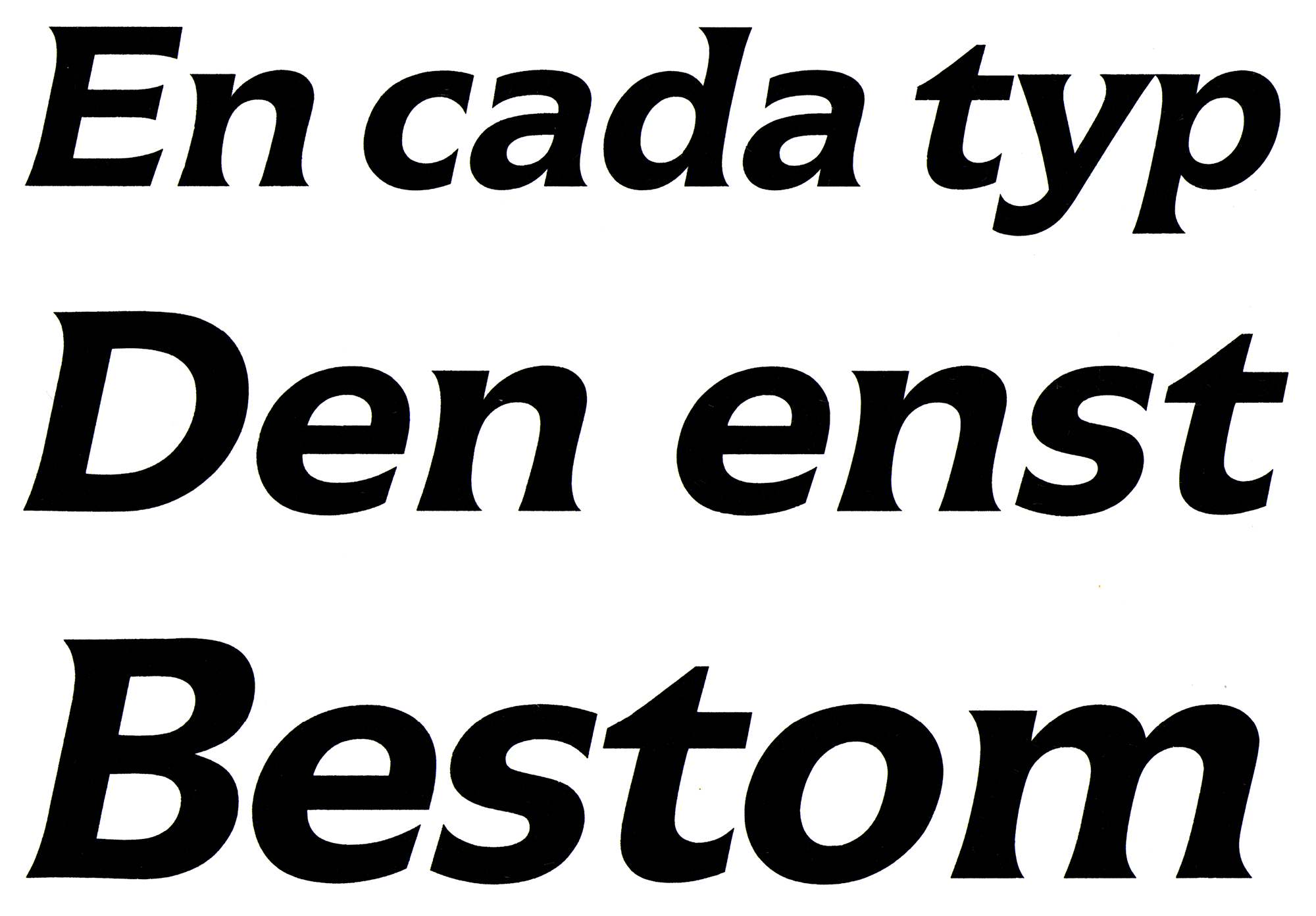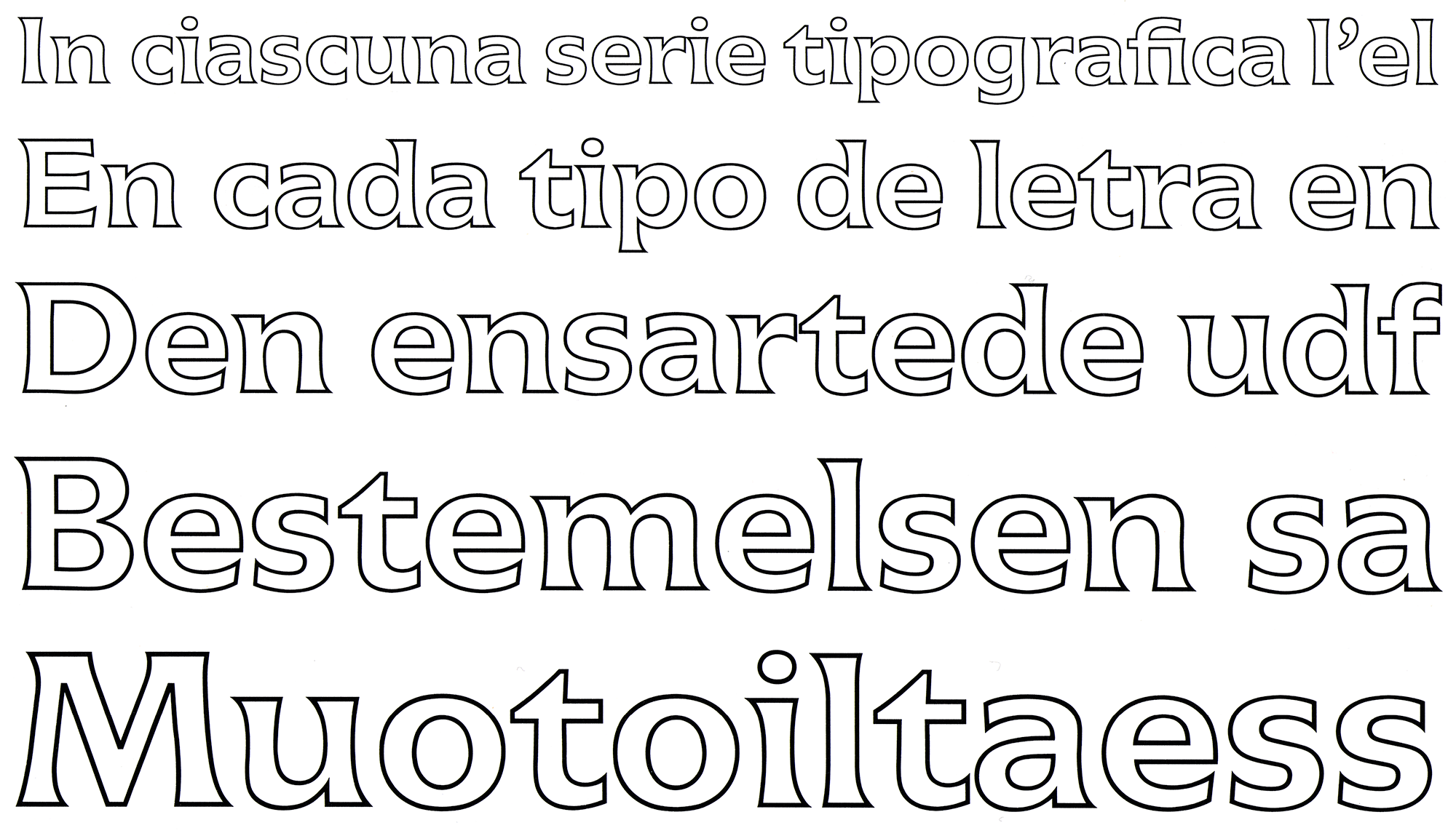
Die Icone ist eine der weniger bekannten Schriften von Adrian Frutiger. Die Schrift erschien 1980 als Fotosatzschrift über Linotype. Charakteristisches Merkmal des Entwurfs ist die starke Kehlung der Stämme. Zur Familie zählen vier Strichstärken mit Kursiven sowie ein lichter Schnitt.
Die Icone ist heute in erweiterten lateinischen Belegung mit Kapitälchen über Linotype verfügbar.